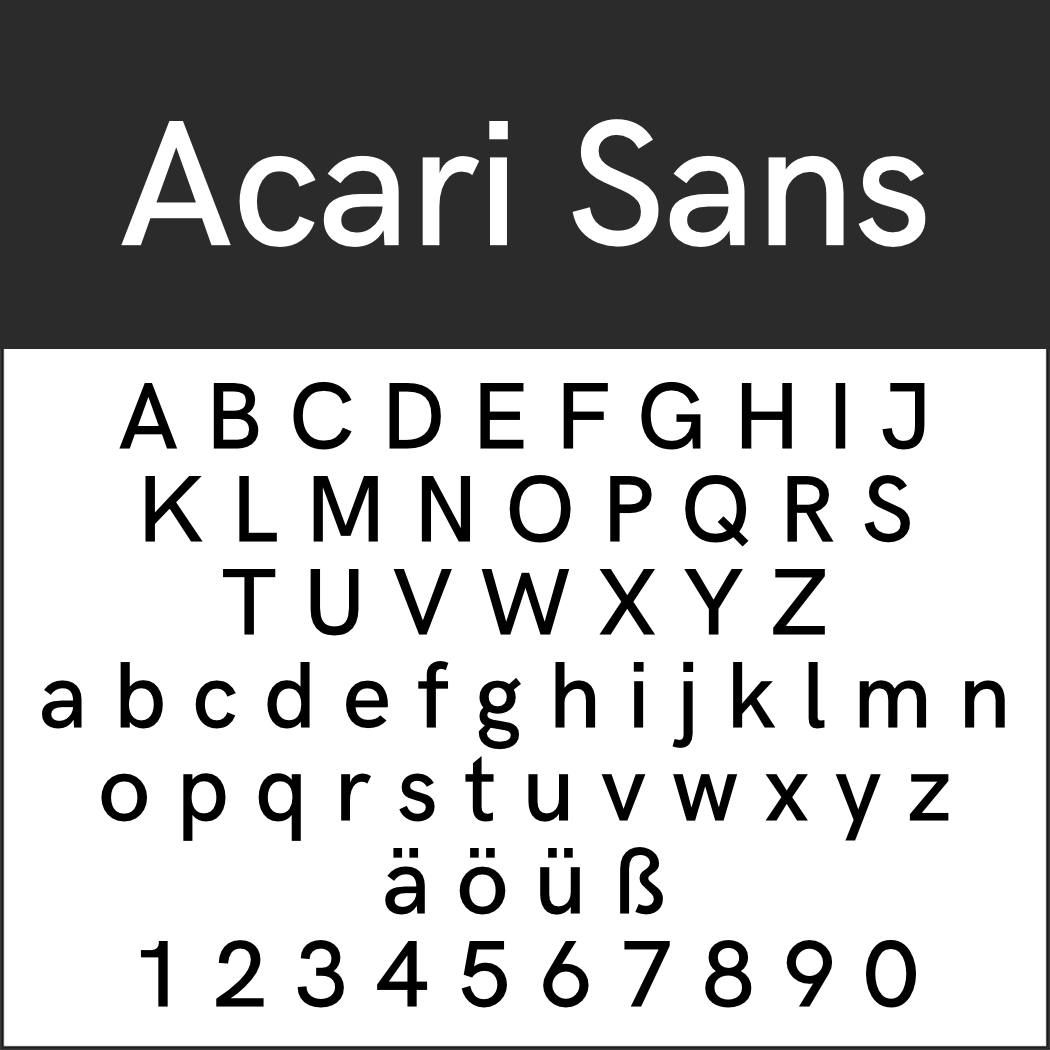
Interessant an der Groteskschrift ist zunächst ihr Name. Außerhalb von Fachkreisen stellt sich die Frage, was an diesen Schriften so „absonderlich übertrieben„, „lächerlich wirkend“ oder „ausgefallen“ sein soll. Keine dieser Bedeutungen aus dem Duden trifft aus unserer heutigen Sicht schließlich darauf zu. Zur Entstehungszeit des Begriffs Groteskschrift im 19. Jahrhundert galten serifenlose Schriften jedoch schon als ausgefallen.
Tatsächlich reicht die Geschichte der serifenlosen Schriften allerdings viel weiter zurück. Beispiele dafür finden sich in der griechischen und römischen Antike und im Mittelalter. Eine Wiederbelebung erfuhren sie mit der Entstehung neuer Wissenschaften im 18. Jahrhundert und vor allem der Industrialisierung im 19. Jahrhundert (s. dazu auch Serifenlose Schriften: Klassiker und kostenlose Fonts).
Laut Typolexikon verwendete der Londoner Typograf Vincent Figgins als erster im 19. Jahrhundert die Bezeichnung „Sans Serif“ für eine Majuskelschrift. Der Name „Groteskschrift“ fiel erstmals im Zusammenhang bei einer serifenlosen Werksatzschrift mit Majuskel- und Minuskelzeichensatz von William Thorowgood im selben Jahr.
„Neu“ an der Groteskschrift war nicht nur, dass sie ohne Serifen auskam, sondern auch ihr fehlender beziehungsweise nur sehr schwach ausgeprägter Kontrast der Strichstärken.
Da natürlich unendlich viele serifenlose Schriften existieren, haben wir unsere Gratis-Beispiele in mehrere Gruppen aufgeteilt.
Sachliche Groteskschriften
Diese Fonts sind sehr sachlich gehalten, enthüllen auf den zweiten Blick aber doch das eine oder andere originelle Detail.
GroteskschriftHK Grotesk
Eine für nahezu alle Fälle: Basierend auf klassischen Sans-Serif-Schriften bietet die HK Grotesk mit insgesamt 20 Schriftschnitten ein breites Einsatzspektrum.
Sinkin Sans
Ähnlich vielfältig mit 18 Schriftschnitten präsentiert sich die Sinkin Sans.
GroteskschriftAcari Sans
Acari Sans (nach einem lateinamerikanischen Fisch benannt) bietet fünf Schriftstärken mit jeweiligen Kursiv-Varianten.
GroteskschriftGlacial Indifference
Für diesen Font ließ sich der Designer von den geometrischen Schriften des Bauhaus inspirieren.
Moderne Groteskschriften
Sans-Serif-Schriften wirken fast alle sehr modern. Wir haben einige herausgegriffen, die sich durch einige Ideen von der breiten Masse etwas abheben.
Wind Sans Serif
Das Charakteristische an Wind Sans Serif sind die scharfen „Schnittkanten“.
GroteskschriftUbuntu
„Ubuntu“ stammt aus den afrikanischen Bantusprachen und bedeutet soviel wie „Gemeinsinn“ – ein passender Name für ein Open-Source-Projekt.
Aclonica
Der gut lesbare Font mit leichtem Strichkonstrast zeigt deutliche Art-déco-Anleihen.
GroteskschriftQuestrial
Die geometrische Questrial harmoniert mit vielen anderen Schriftarten und eignet sich sowohl für Überschriften als auch Fließtexte.
Expletus Sans
Hierbei handelt es sich um einen ausgesprochenen Display Font, der Headlines zu ihrem großen Auftritt verhilft.
Beispiele für elegante Groteskschrift
Auch eine sehr schlichte Schrift kann eine gewisse Eleganz ausstrahlen. Wir haben einfache bis etwas mondänere Fonts ausgewählt.
GroteskschriftNunito Sans
Nunito Sans mit 14 Schriftschnitten basiert auf dem Font Nunito von Vernon Adams.
Rawengulk Sans
Die geometrischen Formen und schwungvolle Details machen die Eleganz von Rawengulk Sans aus.